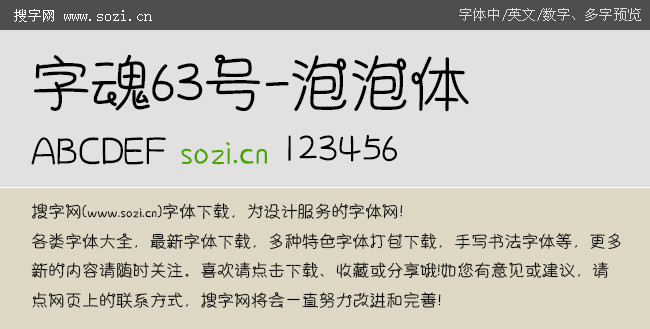
字魂63號(hào)-泡泡體
搜字網(wǎng)提供一款字魂63號(hào)-泡泡體中文字體下載,該字體是一款卡通可愛創(chuàng)意字體,該字體包含6763個(gè)中文、字母、 符號(hào)和數(shù)字,具有有趣、童真、活潑、動(dòng)漫 的風(fēng)格,可以滿足您設(shè)計(jì)上的各種需求,該字體主要用于游戲、動(dòng)漫、H5、包裝、店鋪、活動(dòng)、美食餐飲 等場(chǎng)景。